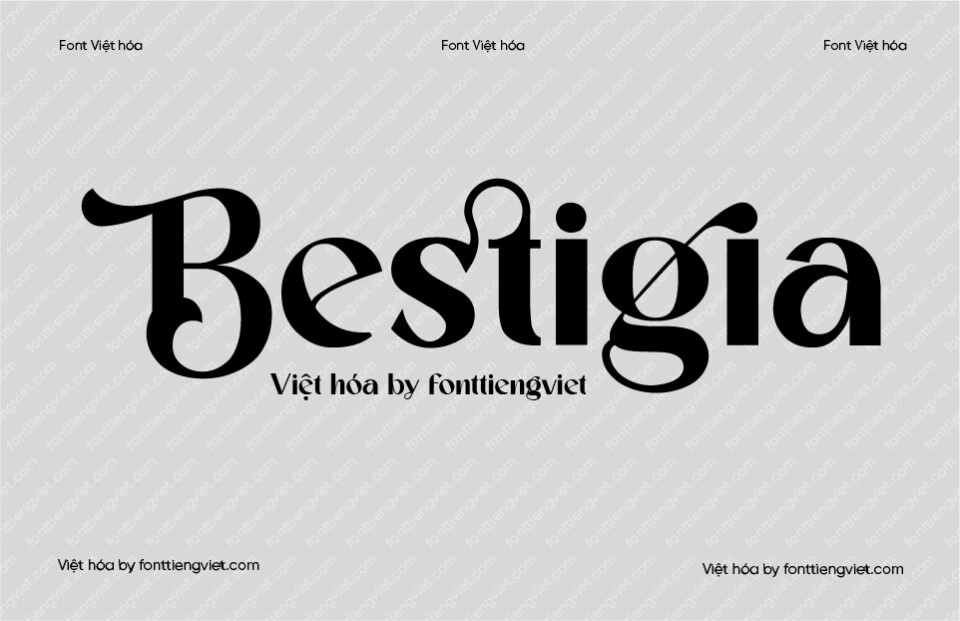
Font Việt hóa 1FTV VIP Bestigia
Font Việt hóa 1FTV VIP Bestigia: Bộ Font Calligraphy Đẳng Cấp Cho Thiết Kế Việt
Giới thiệu về Font Việt hóa 1FTV VIP Bestigia trong thiết kế hiện đại
Trong thế giới sáng tạo nội dung hiện nay, việc lựa chọn một Font Miễn Phí chất lượng luôn là ưu tiên hàng đầu của các bạn học sinh và nhà thiết kế. Font Việt hóa 1FTV VIP Bestigia nổi lên như một hiện tượng nhờ sự kết hợp hoàn mỹ giữa nét vẽ tay uyển chuyển và sự chuyên nghiệp trong cấu trúc chữ. Đây là một bộ font thuộc phong cách Calligraphy hiện đại, mang lại cảm giác sang trọng nhưng vẫn giữ được nét gần gũi, ấm áp. Đặc biệt, phiên bản 1FTV VIP đã được tinh chỉnh kỹ lưỡng về dấu tiếng Việt, giúp người dùng không còn lo lắng về lỗi hiển thị khi soạn thảo văn bản hay làm banner quảng cáo.
Những đặc điểm nổi bật của Font Việt hóa 1FTV VIP Bestigia
Nét chữ thanh mảnh và điệu đà
Font Việt hóa 1FTV VIP Bestigia gây ấn tượng mạnh mẽ với các đường nét thanh đậm rõ ràng. Những đường uốn lượn của bộ font này không quá phức tạp, giúp người xem dễ dàng đọc được nội dung mà vẫn cảm nhận được tính nghệ thuật. Đối với các bạn học sinh đang tập làm báo tường hoặc trình bày slide thuyết trình, đây là lựa chọn tuyệt vời để tạo điểm nhấn cho các tiêu đề quan trọng.
Khả năng ứng dụng đa dạng trong cuộc sống
Không chỉ giới hạn trong các ấn phẩm đồ họa chuyên nghiệp, Font Việt hóa 1FTV VIP Bestigia còn cực kỳ phù hợp cho các thiết kế thiệp mời, bìa sách, hay các câu trích dẫn truyền cảm hứng trên mạng xã hội. Sự mềm mại của Bestigia giúp các thông điệp trở nên nhẹ nhàng và đi sâu vào lòng người hơn. Bạn có thể sử dụng font này để thiết kế áo lớp, làm thiệp chúc mừng thầy cô hoặc trang trí cho các dự án cá nhân tại trường học.
Cách tối ưu hóa Font Việt hóa 1FTV VIP Bestigia cho dự án web
Lưu ý khi sử dụng cỡ chữ và màu sắc
Để Font Việt hóa 1FTV VIP Bestigia phát huy tối đa vẻ đẹp, bạn nên sử dụng ở kích thước lớn cho các tiêu đề (Heading). Do đặc thù là font chữ nghệ thuật, nếu để kích thước quá nhỏ sẽ khiến các nét thanh bị mờ, gây khó đọc. Về màu sắc, những tông màu pastel hoặc màu vàng đồng sẽ làm tăng thêm sự đẳng cấp và tinh tế cho bộ font này. Hãy kết hợp nó với một font chữ không chân (Sans-serif) đơn giản ở phần nội dung để tạo sự cân bằng thị giác hoàn hảo.
Tầm quan trọng của bản Việt hóa chuẩn
Một trong những lý do khiến Font Việt hóa 1FTV VIP Bestigia được yêu thích chính là bộ dấu tiếng Việt được thiết kế vô cùng tỉ mỉ. Các dấu thanh như sắc, huyền, hỏi, ngã, nặng được đặt ở vị trí cân đối, không đè lên các nét chữ chính, đảm bảo tính thẩm mỹ cao nhất cho văn bản tiếng Việt. Điều này cực kỳ quan trọng đối với các nhà thiết kế tại Việt Nam khi muốn truyền tải thông điệp một cách trọn vẹn và chuyên nghiệp nhất.
Lời kết về bộ Font Việt hóa 1FTV VIP Bestigia